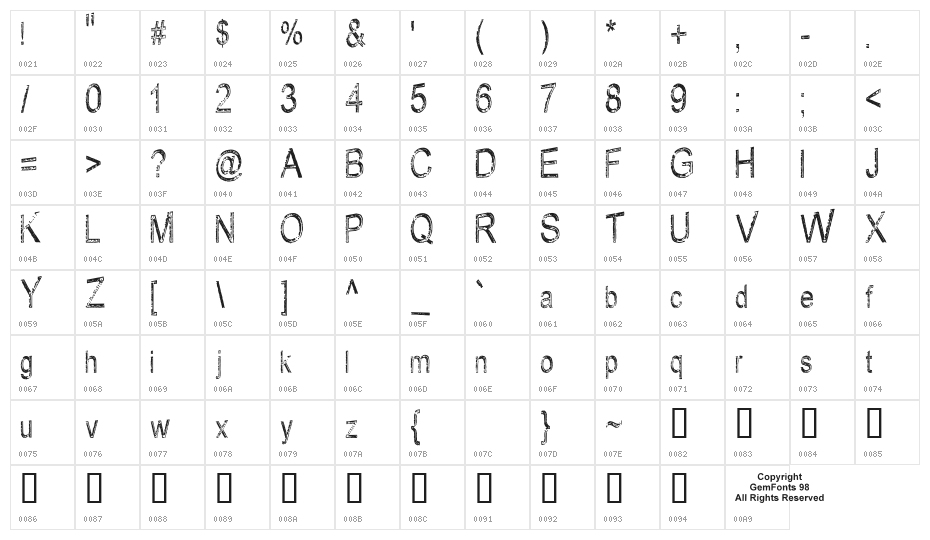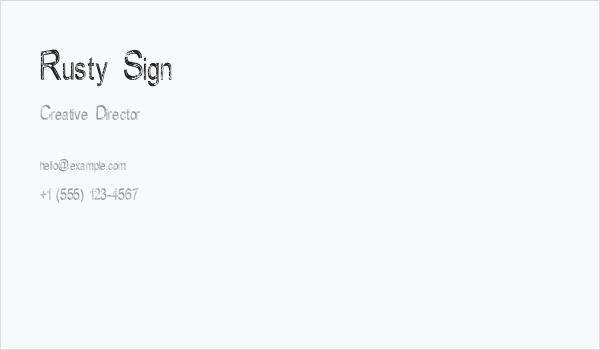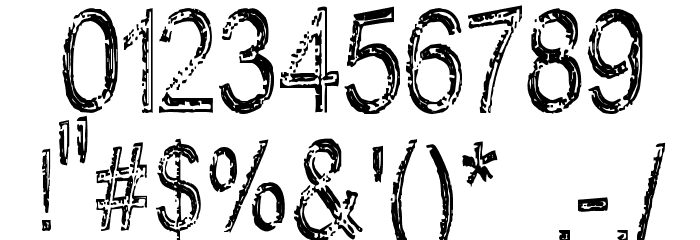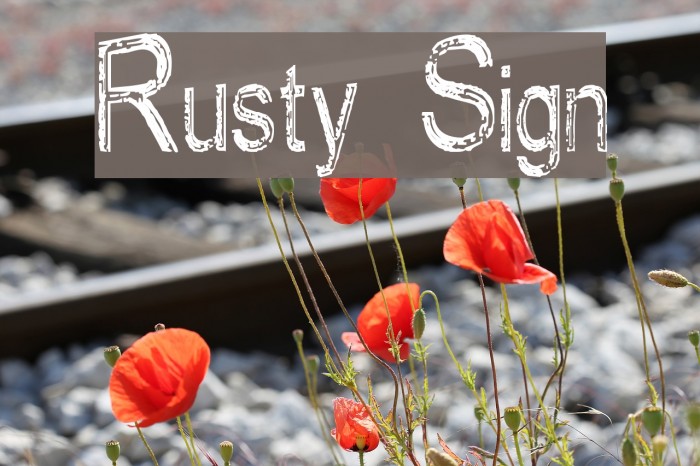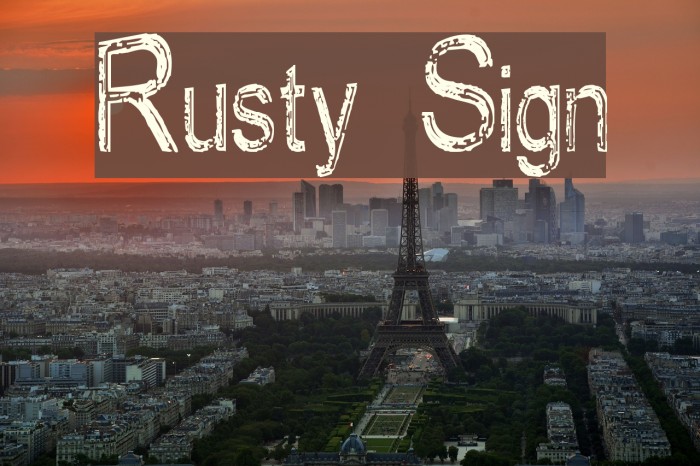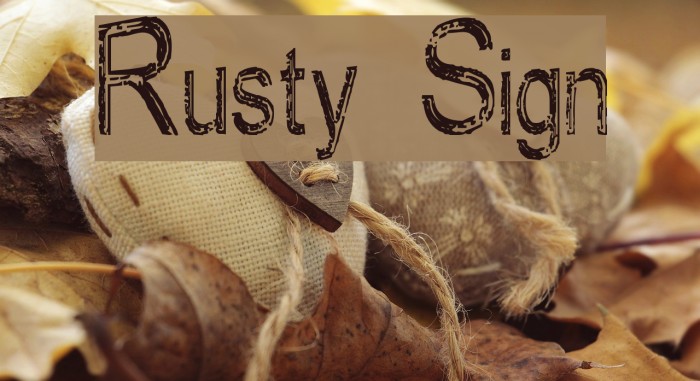
Rusty Sign Font
Fonts by Graham Meade - GemFonts
| Kategorien | Outline |
| Gesamtstil | Vintage |
| Anwendungsfall | Logos, Posters, Branding |
| Vorgeschlagene Projekte | Ideal for vintage-themed posters, industrial design projects, branding for rustic or retro businesses, and any creative work needing a rugged, historical touch. |